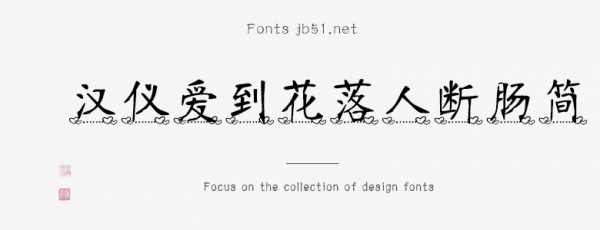
漢儀愛到花落人斷腸簡(jiǎn)是由漢儀字庫出品,字體筆觸適中,字形端正,以心形元素作為點(diǎn)綴,具有很好的視覺感,適合應(yīng)用于藝術(shù)設(shè)計(jì)、平面宣傳設(shè)計(jì)、網(wǎng)頁設(shè)計(jì),書法字帖等領(lǐng)域,需要的朋友可以前來本站下載。